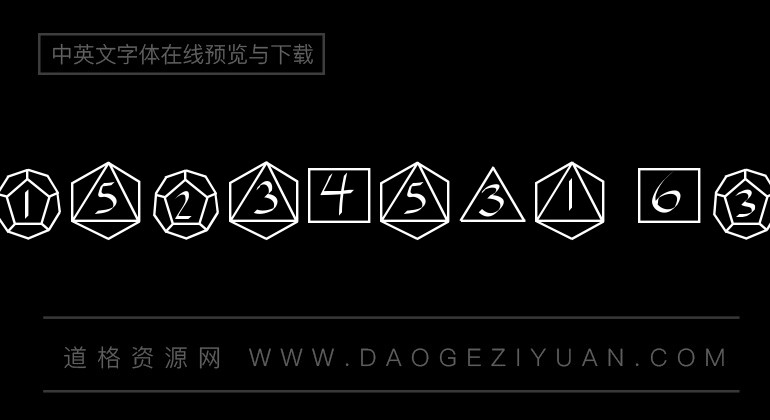
GamingDice Font
GamingDice Font 是一种专门为游戏玩家和制作者设计的字体。该字体的设计灵感来自于骰子,具有独特的外观和设计。它包含了各种点数的骰子,从 D4 到 D20,以及骰子的组合形式,例如 D100 和 D10x10。 该字体的设计旨在使游戏制作者更轻松地创建游戏相关的文本,例如数字、技能值、骰子点数等。它可以用于游戏规则书、角色卡、游戏板块和其他游戏相关材料。 GamingDice Font 是一种 TrueType 字体,可以在大多数计算机上使用。它具有良好的可读性和易于识别的设计,使其成为游戏制作者的理想选择。
GamingDice Font是一款非常不错的手写艺术字体,具有很好的视觉感,适合于文化类的宣传设计、商业类品牌的广告和产品包装设计以及个性化文字排版等较多场景。